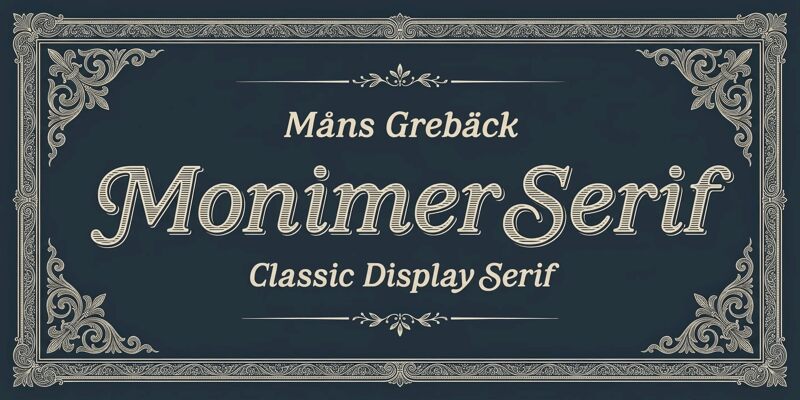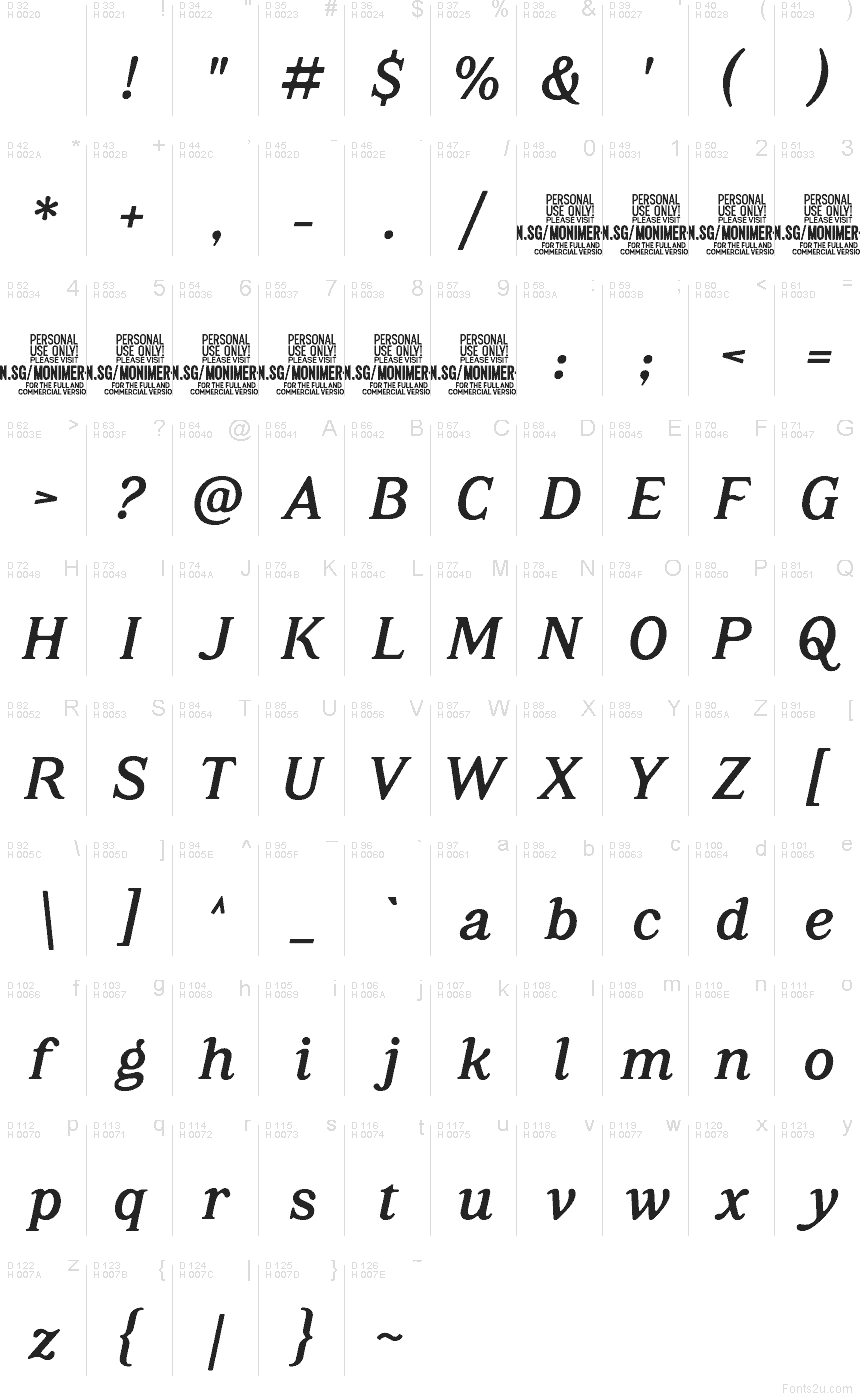
Monimer Serif, de Mans Greback, é uma fonte com serifa gratuita e de alto contraste, com um perfil expressivo e traçado marcante. Curvas amplas e hastes verticais encorpadas estreitam-se em linhas ultrafinas e traços de entrada bem definidos, e a inclinação acentuada dá às letras um movimento ágil para a frente. Suas serifas pontiagudas são especialmente distintas.
O meio editorial oferece a essas formas dramáticas um espaço perfeito em revistas de moda, capas de livros e cartazes de eventos artísticos, onde a variação na espessura dos traços proporciona tanto elegância quanto tensão. As embalagens de luxo são outro excelente campo de uso, sobretudo para marcas de perfumes ou doces finos que buscam uma composição que lembre o trabalho formal a bico de pena e o estilo editorial teatral.
Monimer Serif é uma fonte serifada display.